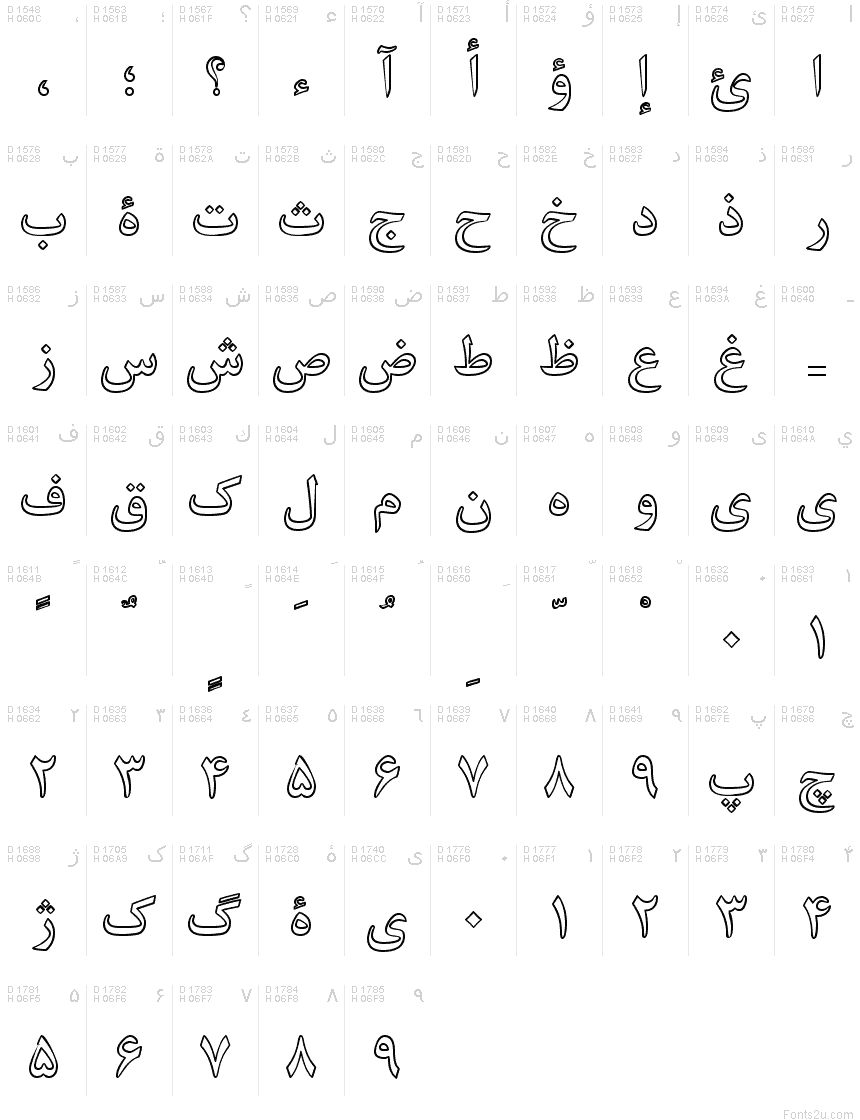
B Nazanin Outline di Borna Rayaneh è un carattere arabo gratuito con uno stile "outline" dal carattere calligrafico calmo e libresco. Le lettere fluiscono con un ritmo costante e connesso, utilizzando tratti aperti e forme arrotondate che rendono il font leggero anziché pesante, conferendo un'impressione formale ma non rigida.
È adatto a testate editoriali, manifesti culturali, packaging, titoli e progetti di identità visiva in cui uno stile arabo delineato risulta più sfumato rispetto a un riempimento pieno. Essendo un font gratuito, è ideale anche per copertine, grafiche per eventi e monogrammi, specialmente quando si desidera che le connessioni fluide della calligrafia sostengano da sole la composizione.